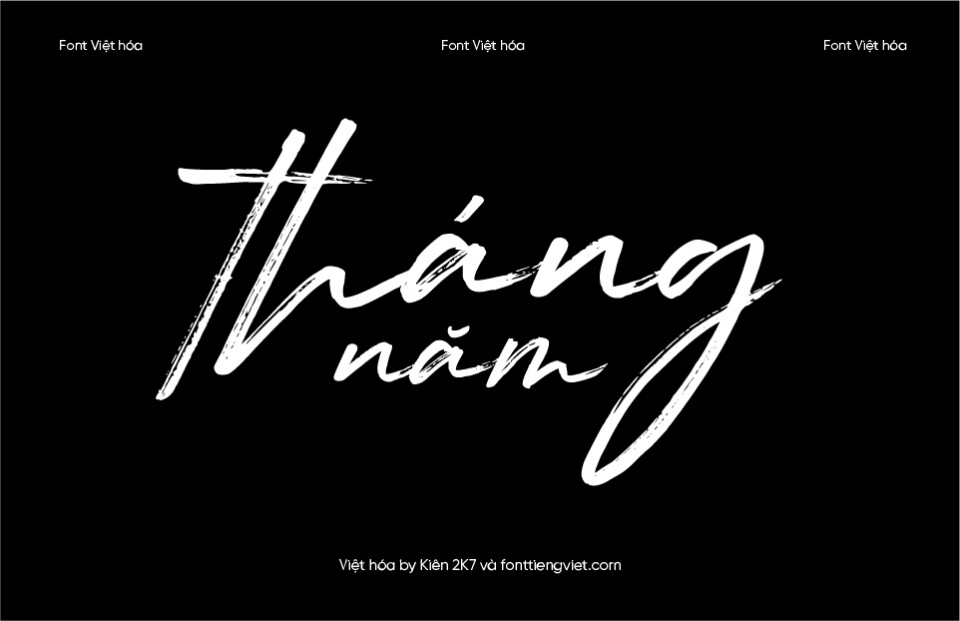
Font Việt hóa 1FTV VIP Handstand – Brush – Nghệ thuật chữ viết tay sáng tạo
Giới thiệu về Font Việt hóa 1FTV VIP Handstand – Brush
Trong thế giới thiết kế đồ họa hiện đại, việc tìm kiếm một bộ Font Chữ mang đậm dấu ấn cá nhân và sự phóng khoáng luôn là ưu tiên hàng đầu. Font Việt hóa 1FTV VIP Handstand – Brush chính là câu trả lời hoàn hảo cho những ai yêu thích phong cách Brush Script đầy năng động. Bộ phông này không chỉ giữ nguyên được vẻ đẹp thô mộc, tự nhiên của những nét cọ vẽ tay mà còn được tối ưu hóa hoàn toàn cho bảng mã tiếng Việt, giúp người dùng dễ dàng thể hiện ý tưởng mà không lo lỗi font.
Đặc điểm nổi bật của Font Việt hóa 1FTV VIP Handstand – Brush
Phong cách tự do và linh hoạt
Đúng như tên gọi Handstand, bộ font này mang đến một cảm giác bay bổng, nghịch ngợm nhưng cũng không kém phần chuyên nghiệp. Các đường nét thanh đậm được đan xen một cách ngẫu hứng, tạo nên sức sống cho từng con chữ. Font Việt hóa 1FTV VIP Handstand – Brush rất phù hợp cho các dự án thiết kế bìa sách, poster sự kiện trường học, hoặc các ấn phẩm truyền thông dành cho giới trẻ.
Tính ứng dụng cao trong học tập và giảng dạy
Đối với giáo viên và học sinh, việc sử dụng các phông chữ sáng tạo giúp bài giảng trở nên sinh động hơn. Bộ font này hỗ trợ đầy đủ các dấu tiếng Việt, đảm bảo tính thẩm mỹ cao khi trình bày nội dung trên các nền tảng số hoặc in ấn. Bạn có thể sử dụng nó để trang trí thiệp mời, làm tiêu đề cho các bài thuyết trình hoặc thiết kế áo đồng phục lớp đầy cá tính.